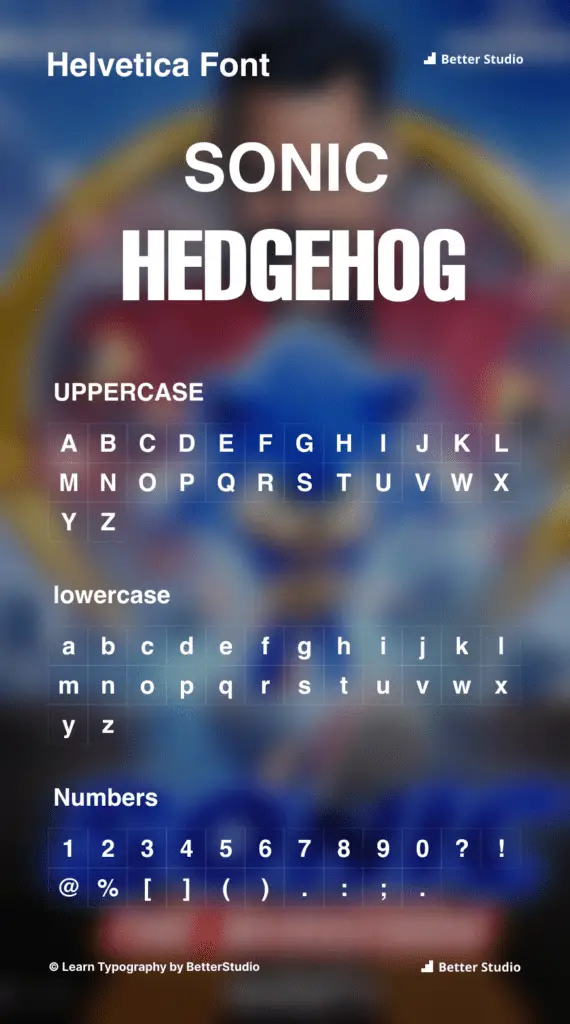
Czcionka Sonic Hedgehog
Czcionka plakatu filmowego Sonic Hedgehog ma unikalny i charakterystyczny styl, który oddaje istotę filmu, co jest bardzo charakterystyczne dla plakatów filmowych Sonic Hedgehog pod względem krojów pisma.
Oprócz tego, że stał się symbolem serii, obraz był również szeroko stosowany w innych mediach, takich jak komiksy i gry wideo, odkąd został stworzony, udowadniając, że jest zarówno ponadczasowy, jak i kultowy.
Jakiej czcionki używa Sonic Hedgehog?
Wiadomo, że „ Helvetica and Nise Sonic Sega ” to nazwa czcionki logo Sonic Hedgehog.
Czcionka Sonic Hedgehog
Alternatywy i podobne style czcionek do Helvetica i Nise Sonic Sega
Lista 5 alternatywnych czcionek, które są podobne pod względem projektu i zastosowania do czcionek Helvetica i Nise Sonic Sega, została opracowana do rozważenia.
- Czcionka Monotype Corsiva
- Czcionka Copperplate Gothic Bold
- Czcionka uderzeniowa
- Czcionka Haettenschweiler
- Czcionka chillera
Kto zaprojektował czcionkę Sonic Hedgehog?
Czcionka oparta na postaci Sonic Hedgehog została zaprojektowana przez Katharine Worsley. Jest doświadczoną projektantką czcionek, która pracowała między innymi nad popularnymi czcionkami, takimi jak Helvetica i Nise Sonic Sega.
Oprócz swoich ukochanych krojów używanych w grach takich jak Call of Duty, Guitar Hero, a nawet The Sims, pracowała również nad wieloma krojami związanymi z grami wideo.
To jej doświadczenie w projektowaniu zabawnych i interaktywnych krojów pisma sprawiło, że jest obecnie jedną z najbardziej poszukiwanych projektantek w branży.
Opis Sonic Hedgehog
Znany ze swojej szybkości i postawy, Sonic the Hedgehog to kultowa postać z gier wideo, która stała się najbardziej znana dzięki grze Sonic z 1991 roku. Jest niebieskim jeżem w pomarańczowych butach i szybkim jeżem o wielkiej osobowości.
Dzięki tysiącom tytułów spin-off i programów telewizyjnych od czasu swojego pojawienia się, maskotka Sega wyrobiła sobie markę w branży rozrywkowej, służąc jako sposób na łączenie pokoleń dzieci i dorosłych poprzez swoje przygody.
Projekt logo Sonic z oryginalnej gry został dostosowany do tej czcionki, która została wyróżniona kursywą, aby uchwycić charakterystyczny wygląd Sonica, który nie może lepiej pasować do symbolizowania postaci.
Jest to wysokiej jakości czcionka, która jest natychmiast rozpoznawalna ze względu na swój klasyczny styl i jest często używana w logo, tytułach, plakatach i innych materiałach drukowanych związanych z grami Sonic i domem.
Czcionka Sonic Hedgehog wywarła ogromny wpływ na całą kulturę popularną, a miliony fanów Sonic z całego świata używają jej do tworzenia własnych dzieł fanów, t-shirtów i innych produktów, aby wyrazić ich miłość do postaci i jej przygód.